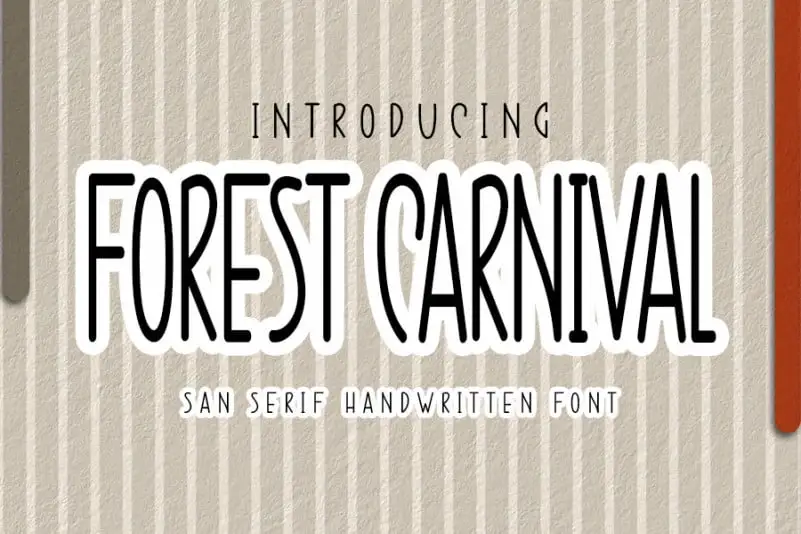
Forest Carnival Script Font – Download Grátis
Forest Carnival Script Font é uma fonte à mão livre que preserva a elegância tradicional do guache ao mesmo tempo que traz uma sensação contemporânea e fresca. Com seu charme clássico, esta fonte é perfeita para quem busca algo diferente no design de letras. A versatilidade dessa fonte faz dela um recurso ideal para inúmeras idéias criativas, adaptando-se perfeitamente tanto ao uso em cartazes e títulos como à produção de materiais de embalagem ou assinaturas. Ideal para designers que buscam adicionar personalidade aos seus projetos, Forest Carnival Script Font não apenas traz uma nova dimensão às páginas impressas, mas também oferece um toque único que encantará os consumidores. Essa fonte é perfeita tanto para estilos clássicos quanto modernos, tornando-a uma escolha ótima para aqueles que querem destacar seus projetos de design gráfico. Sua utilização em materiais de embalagem ou assinaturas pode trazer um toque distintivo que certamente chamaria atenção e criaria um impacto atraente.